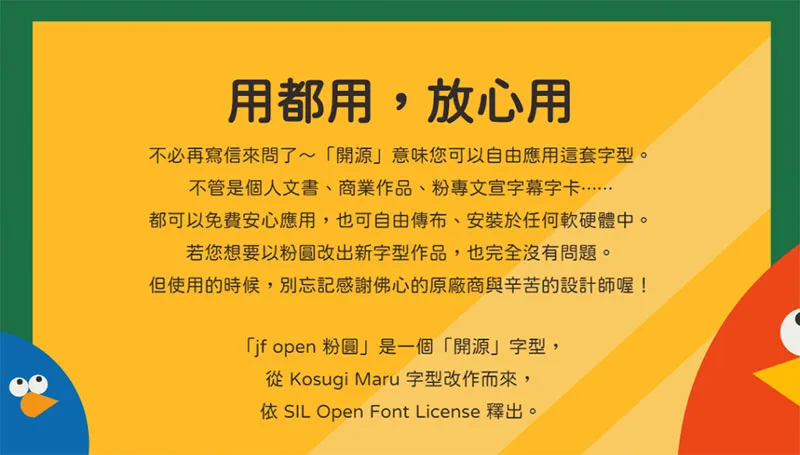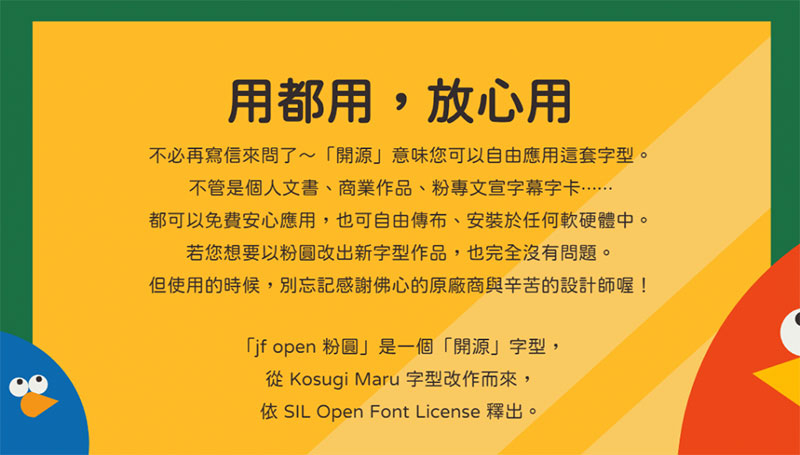
「jf open粉圓」是基於小杉圓體(Kosugi Maru)改作,由justfont設計師針對臺灣日常應用加以優化的開源字型,以OFL 1.1開源授權釋出,歡迎大家自由應用、自由優化、自由改作!
在「小杉圓體」的基礎上,針對臺灣的使用與排版需求,在原有的日文字型基礎上,增加了臺灣常用字、注音符號,並修訂排版設定,甚至增加了臺灣拼音,以適應臺灣的使用需求。設計師改進了原有字體的品質,讓你的排版更美麗!新的「jf open 粉圓」字型大致來說,做了以下改變:
優化設計針對原本字符粗細不均勻、佈局不盡理想的狀況調整、優化。
排版-調整「小杉圓體」原為日文字型標點符號設計,「jf open 粉圓」則改為繁體中文標點符號設置。
增補字符補齊日文字型中所缺乏的臺灣常用漢字共1,484 字,另設計注音符號及臺灣拼音符號。